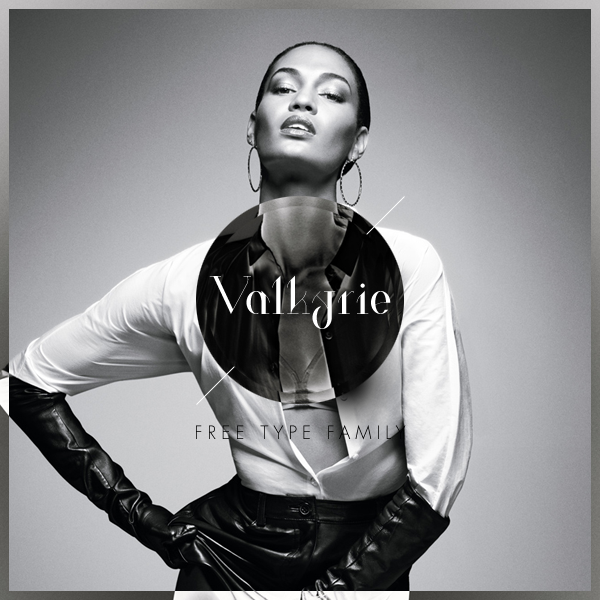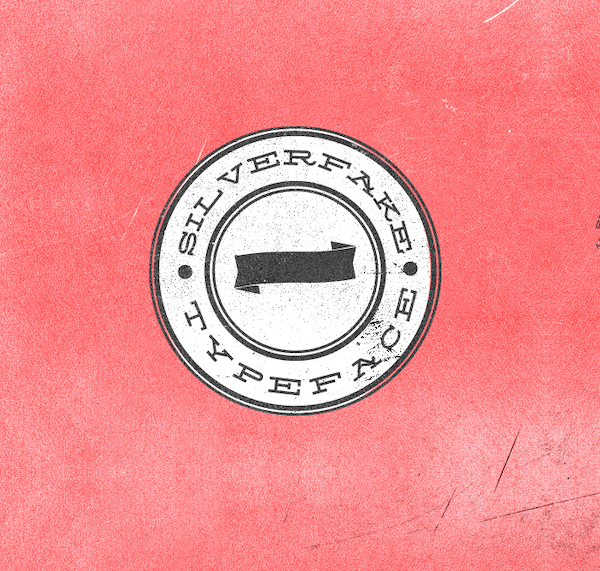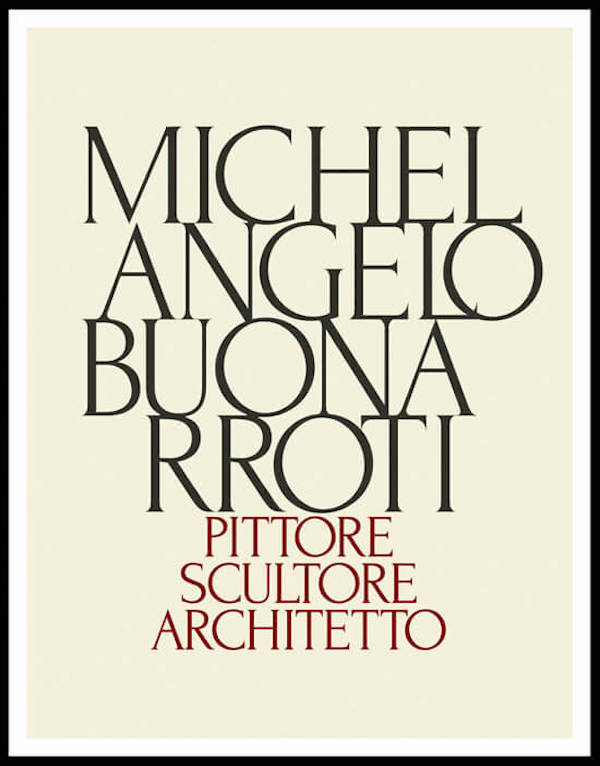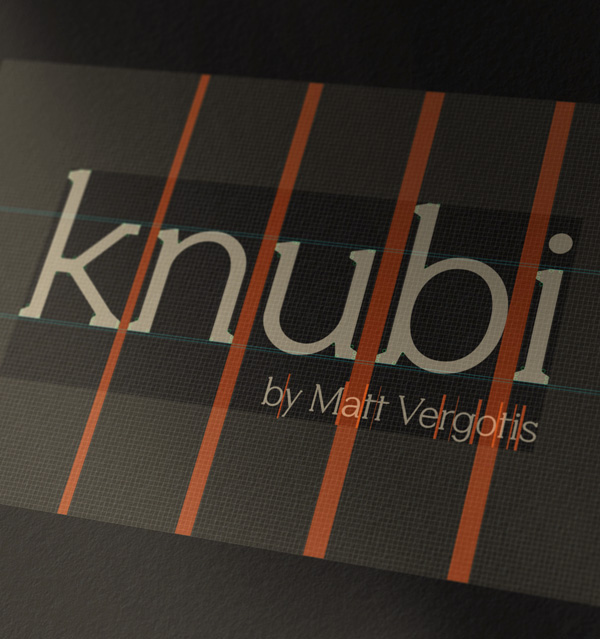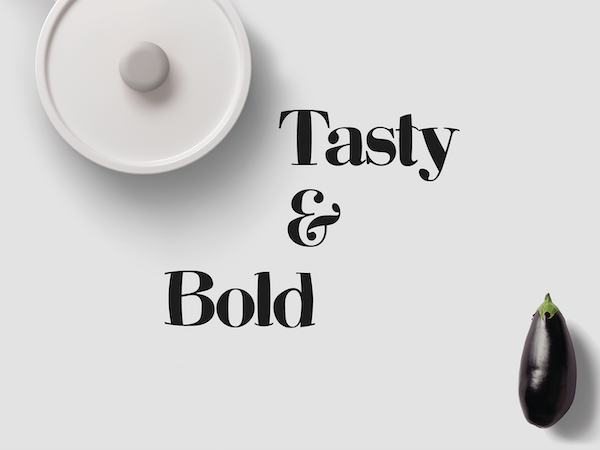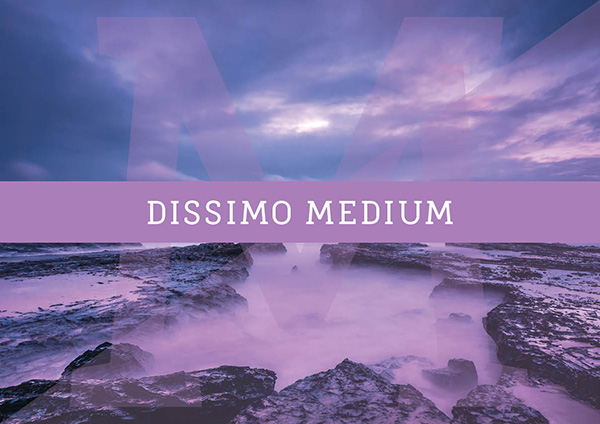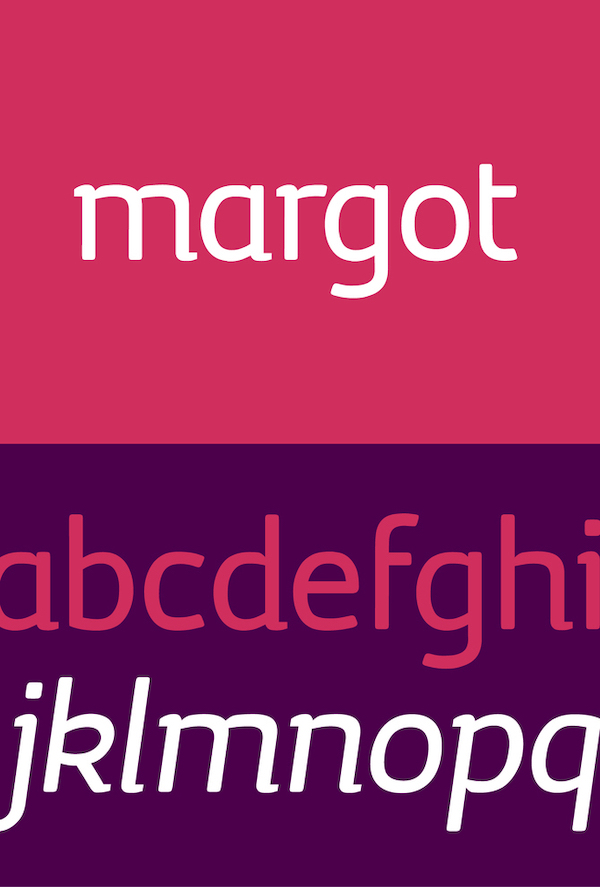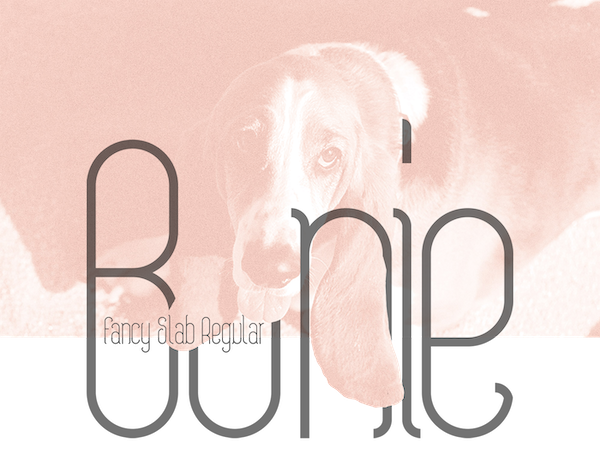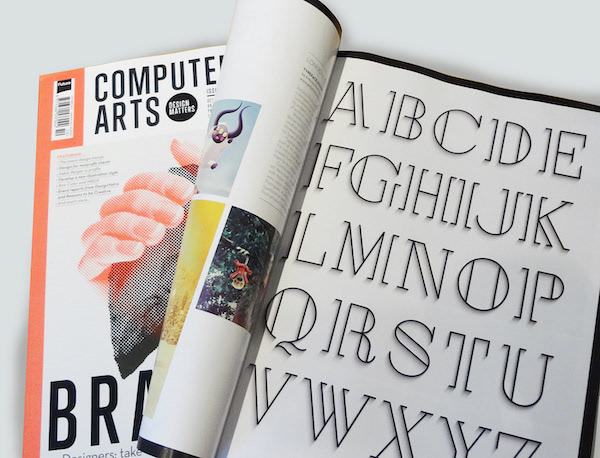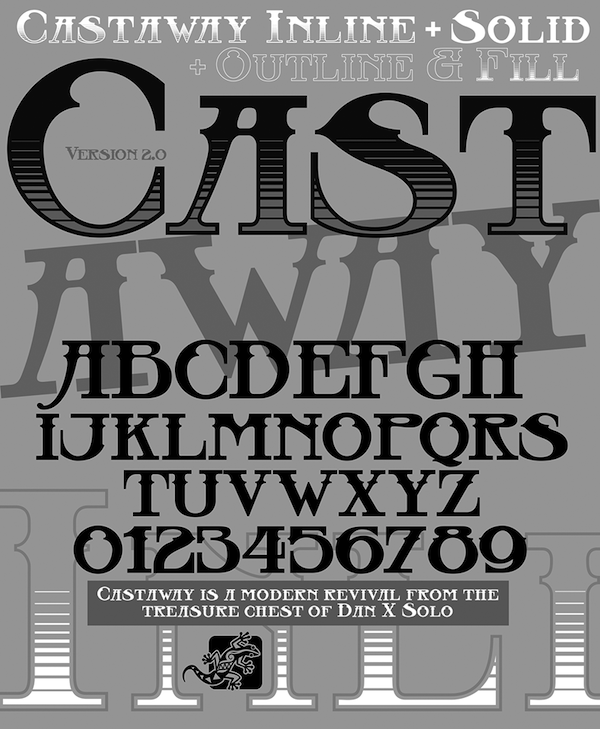
25 typographies à empattements gratuites pour vos créations
Il existe deux grandes familles de typographies : celle à empattement (ou sérif) et celle sans empattement (ou sans-sérif).
L’empattement c’est la petite extension à l’extrémité des caractères. Son origine trouverait son explication dans la trace laissée lors de l’écriture manuscrite.
Les typographies à empattements, souvent utilisées en imprimerie, donnent une image de prestige, de raffinement et d’élégance à vos créations. Le choix de sa typographie pour ses créations doit être une démarche réfléchie, chaque police véhiculant un message spécifique.
Les polices à empattements fluidifient la lecture et sont couramment utilisées dans les textes longs. Attention, en dessous de 8 pt, elles sont difficilement lisibles !
Voici donc des typographies avec Sérif qui, non seulement, sont gratuites, mais qui sont surtout très tendance !
Butler est un savant mélange entre les polices Dala Floda et Bodoni. Cette typo réussit l’exploit d’être à la fois classique et moderne ! On l’aime sur les affiches, les très gros titres ou encore dans les articles de fantaisie !
Margot est une typo sérif tout en courbe, joyeuse et dynamique, qui séduira un public féminin. Particulièrement optimisée pour les grandes tailles, elle est parfaite pour les gros titres et les affiches.
Cette police sérif a un petit côté ludique qui plaira à un public jeune. Elle est optimisée pour une intégration web.
Voici une typographie à empattements très moderne, idéale pour les titres d’affiches !
Les bords arrondis de cette police sérif cassent sa structure un peu rigide et offrent un contraste dynamique.
Rude porte bien son nom, on la sent sauvage et indomptable et pourtant cette typo à empattement est 100 % gratuite !
Arber est une typo sérif vintage, son aspect très naturel s’intègre parfaitement sur une affiche, un logo ou un gros titre.
Voici une police sérif contemporaine et moderne qui pourtant garde un petit aspect rétro ! Vous ne la trouverez qu’en majuscule.
Vous trouverez cette police sérif seulement en versions Regular et Fill. Très originale, elle allie élégance et raffinement, parfaite dans le domaine du luxe.
D’inspiration industrielle, Geared est une typographie à empattements disponible en Thin, Regular, Bold et Extrabold. Elle est gratuite exclusivement pour un usage personnel.
Patua One incarne la douceur et la féminité avec ses courbes et ses rondeurs.
Cette police sérif a l’avantage d’être tombée dans le domaine public, vous pourrez l’utiliser à loisir dans toutes vos créations.
Voici une typographie à empattements qui s’adaptera à tous vos projets, elle est claire et simple, et à un rendu très professionnel.
Si vous cherchez une police glamour, Voga est faite pour vous ! Élégante et sexy, cette typo s’offre à vous en Regular, Medium et Bold.
Valkyrie incarne le luxe et le raffinement, elle s’affiche sur les créations d’un grand nombre de marques prestigieuses.
Dissimo est une police à empattements sobre, elle peut convenir pour toutes sortes de créations. Attention, seulement sa police Medium est gratuite !
Gratuite pour un usage personnel, cette typographie à empattements sobre et moderne se prête tout à fait au domaine de l’industrie et de l’informatique.